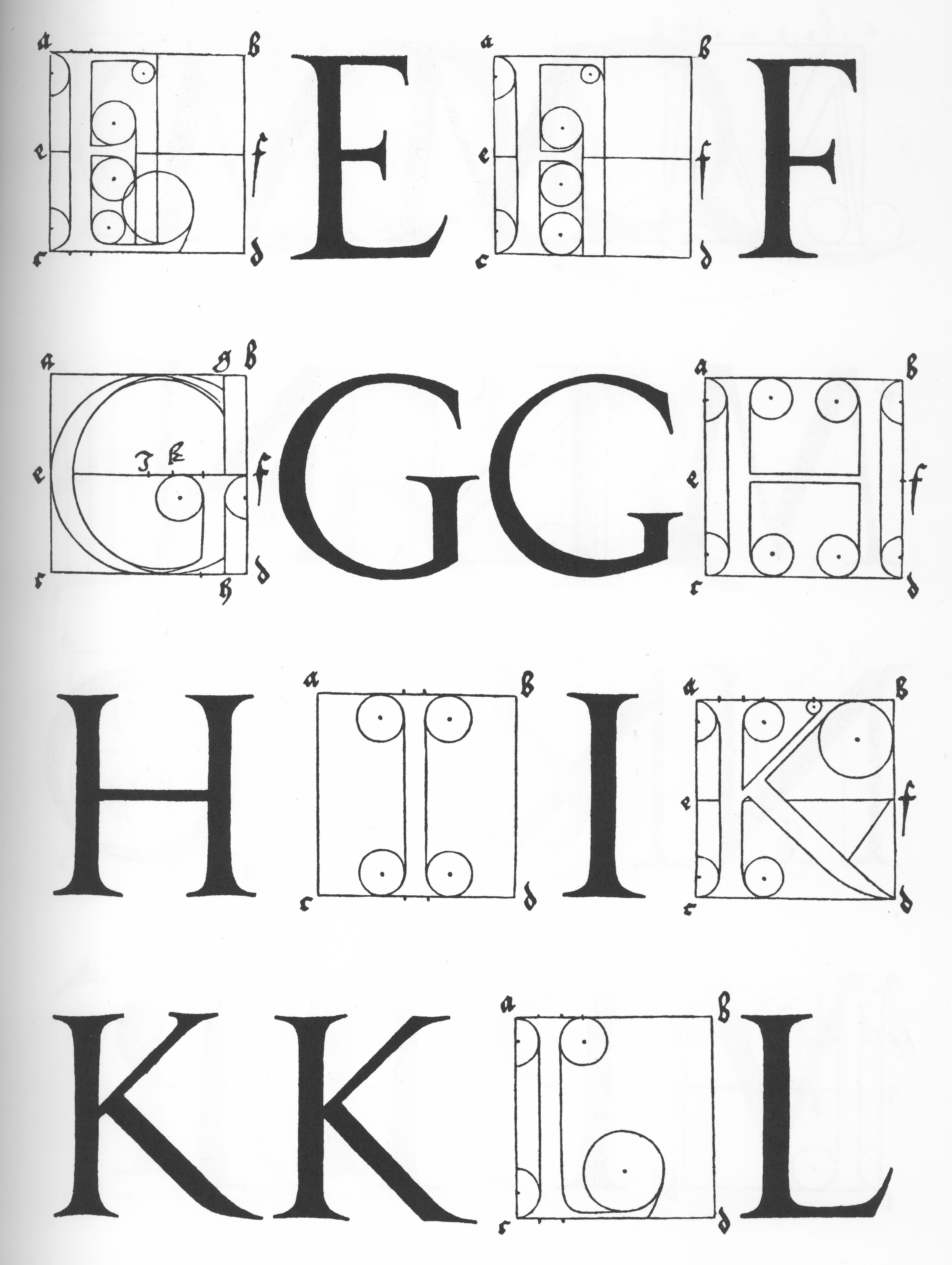
Особенности построения шрифтов
Оптические иллюзии
Чередование штрихов в буквах
Изучение прототипа
Прописные буквы
Чтобы правильно подойти к вопросу конструирования шрифта, следует знать некоторые нюансы, которые необходимо учитывать в своей работе.
Оптические иллюзии
В шрифте часто наблюдаются явления, которые принято называть оптическими иллюзиями. Прежде чем рассмотреть это понятие применительно к буквам, приведем несколько довольно известных примеров.
На рис. 1 линия а равна по длине линии б, но кажется длиннее.
Линии г и д параллельны, но благодаря пересечению диагональными линиями кажутся
непараллельными. Если вертикальную линию е (слева) разделить точно посредине,
то зрительно будет казаться, что оба отрезка не равны между собой — верхний
больше нижнего. Путем перенесения точки деления на линии е (справа) несколько
вверх можно добиться такого положения, когда оба отрезка будут восприниматься
как равные, хотя в действительности этого не будет.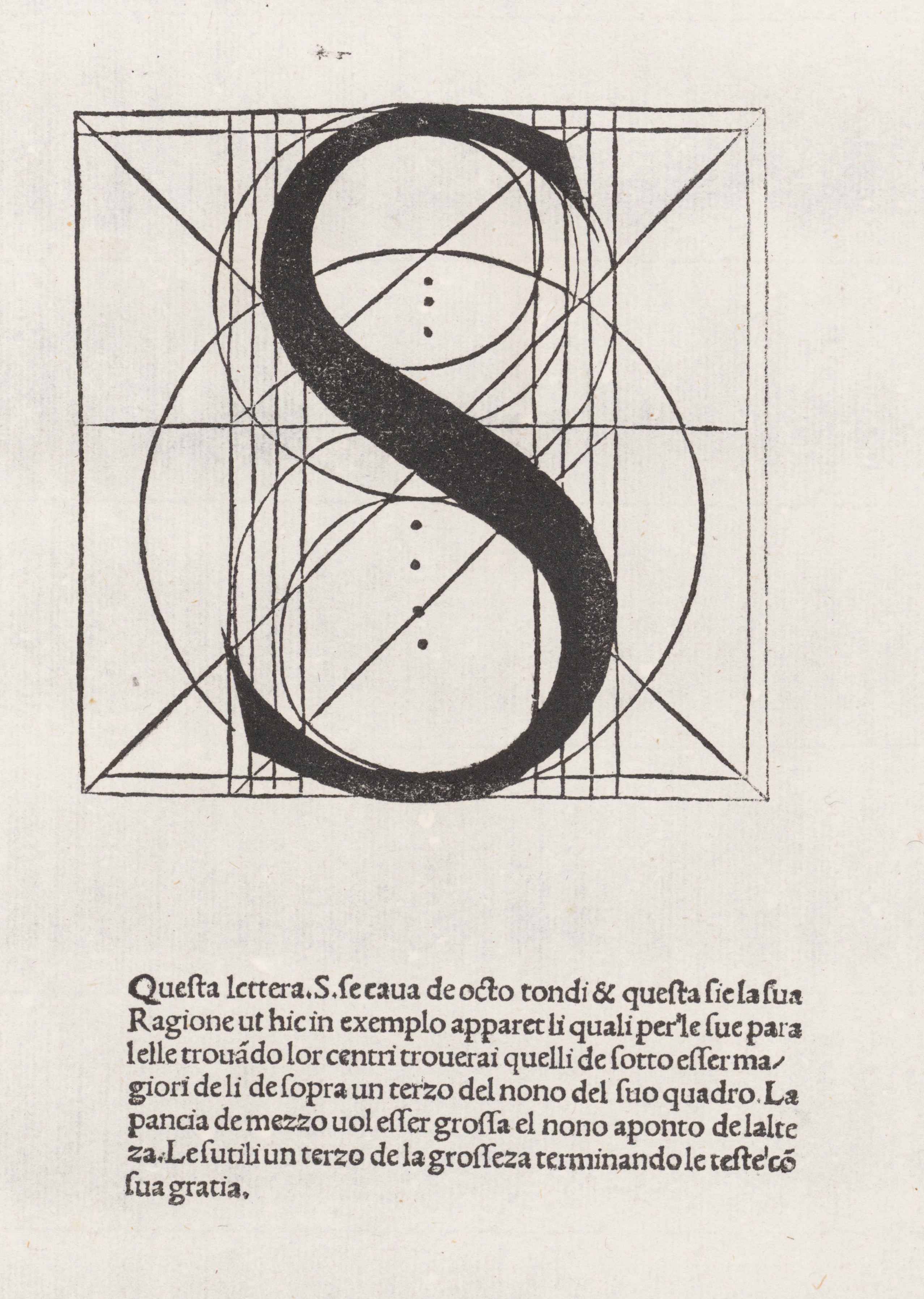
В шрифтах в ряде случаев мы также встречаемся с оптическими иллюзиями. Буквы, имеющие остроконечные формы, кажутся ниже других букв. На рис. 2 (сверху) буква А кажется менее высокой, чем буква Н. Это происходит потому, что буква А в данном примере имеет остроконечную вершину и касается верхней линии строки лишь в одной точке. Чтобы зрительно выровнять такую букву по росту с другими буквами, нужно немного вынести ее острую часть ее за линию строки (показано снизу). Это касается всех букв, имеющих такие вершины.
Круглые буквы, например буква О, также будут казаться ниже, чем прямые. Чтобы
такие буквы зрительно выровнять с прямыми, их приходится несколько увеличивать
по росту, выпуская немного за пределы верхней и нижней линий строки.
В буквах Н и И оптические иллюзии сказываются следующим образом: если обе буквы взять одинаковой ширины, то буква И будет казаться несколько уже, чем буква Н. Это происходит потому, что диагональный элемент в букве И занимает больше внутрибуквенного пространства, чем горизонтальный штрих в букве Н. В связи с этим в некоторых случаях букву И необходимо делать по ширине чуть больше, чтобы зрительно выровнять ее с буквой Н (рис. 3).
Кроме оптических иллюзий, которые условно можно назвать линейными, так как они касаются изменения размеров изображения, следует различать оптические иллюзии, которые можно назвать пространственными.
На рис. 4 изображены круги разной величины в одинаковых
рамках. Если мы обратим внимание на пространственное положение этих кругов по
отношению к рамкам, то заметим, что в первом случае круг кажется лежащим за
рамкой, во втором случае — перед рамкой, в третьем — в одной плоскости с рамкой.
Еще один пример. На рис. 5 фигура а напоминает собой каплю. С этим понятием у нас связано представление об объеме, имеющем ту или иную рельефность. Поэтому такая форма кажется нам предметной.
В черном цвете мы ощущаем светотеневую моделировку формы. Такое изображение подавляет окружающий фон и кажется лежащим на поверхности бумаги.
Другое впечатление производит фигура б. Со всех сторон на нее активно наступает белый цвет. Черное изображение в значительной степени лишено объемности. Такая форма кажется несколько углубленной в бумагу, лежащей за ее поверхностью.
В первом случае черный цвет вследствие возникновения иллюзий светотеневой моделировки формы будет казаться менее насыщенным, чем во втором.
Подобные явления пространственных оптических иллюзий и различного качественного состояния черного цвета можно наблюдать и в буквах.
По аналогии с предыдущими примерами фигура в, изображающая основной штрих буквы,
будет казаться рельефом, лежащим на поверхности бумаги.
Объемность этого элемента
буквы возникает из-за наличия массивных округлых форм, имеющих сходство с фигурой
а.
Шрифты такого типа, как правило, малоконтрастны, имеют массивные закругленные засечки, основные штрихи очень предметны. В малоконтрастных шрифтах буквы предметны, черный цвет не играет активной роли.
В одних случаях характер рисунка элементов создает буквам впечатление объемности